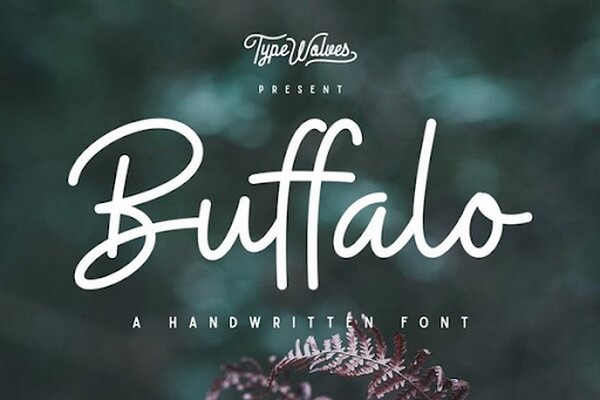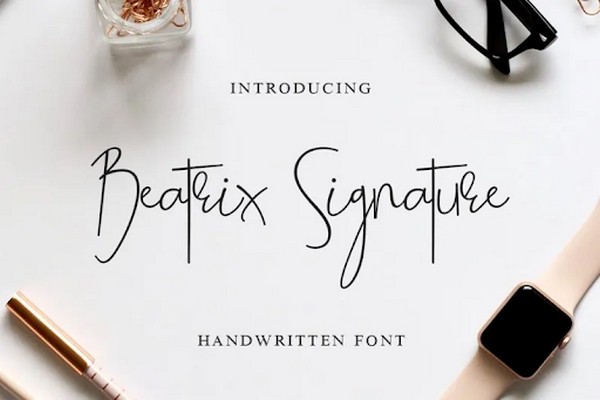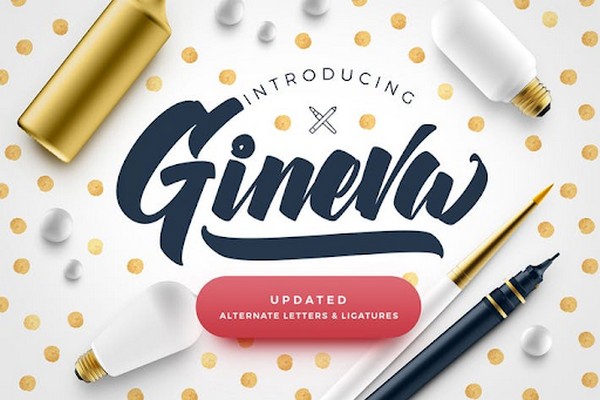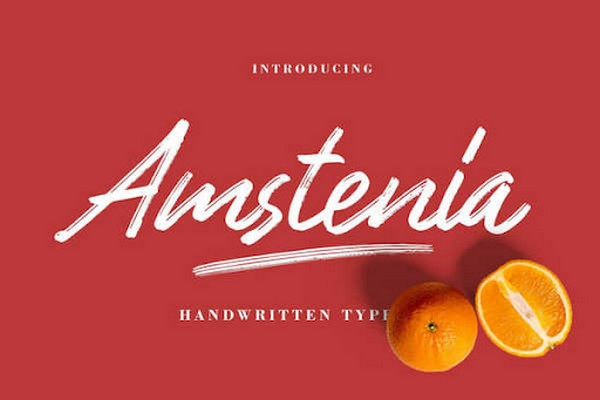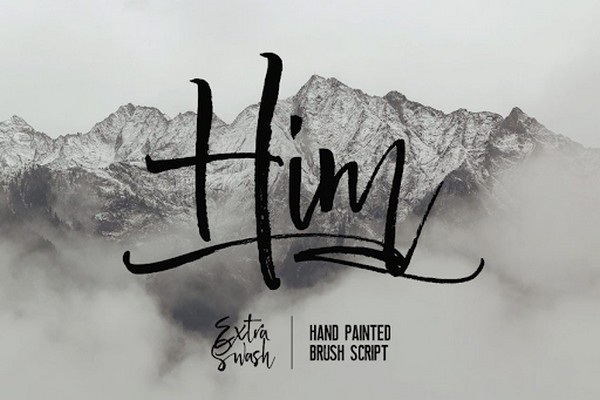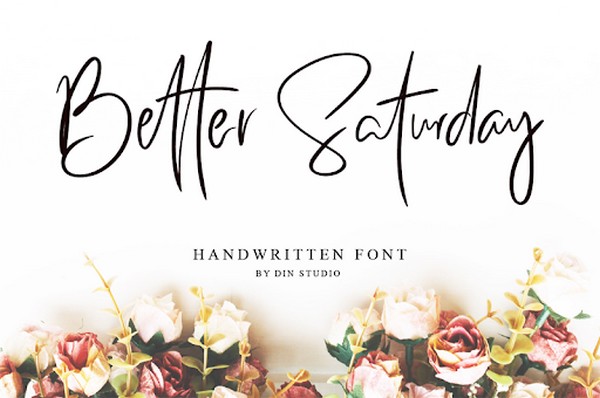
Font chữ viết tay là gì? Top những font chữ viết tay đẹp nhất hiện nay
Có thể nói chữ viết tay là một loại nghệ thuật vô cùng đẹp mắt đối với bất kể ai quan tâm đến chữ thư pháp. Những người “thợ” đã rất tỉ mỉ và hello88.con để có thể tạo ra những nét chữ đẹp mang đầy cảm xúc. Trong heloo88 nói riêng bạn cũng có thể sử dụng những font chữ viết tay để giúp sản phẩm của mình có tính nghệ thuật hơn. Hãy cùng chúng tôi tìm hiểu font chữ viết tay là gì và top những font chữ viết tay đẹp qua bài viết dưới đây bạn nhé!
Font chữ viết tay là gì?
Font chữ viết tay là một bộ font chữ mà khi ta đánh chữ vào thì nó sẽ hiện ra các dòng chữ giống như người thật viết. Nếu như các font chữ mặc định của Windows như Time New Roman, Arial không thể tạo nên cảm xúc gì thì các font chữ viết tay sẽ cho bạn cảm giác thân thiện, gần gũi trong từng đường nét. Còn gì tuyệt hơn khi mà heloo88 một tấm thiệp mà dùng font chữ viết tay. Cầm tấm thiệp trên tay người đọc sẽ có cảm giác vô cùng gần gũi và thân thiết.
Chữ viết tay với đặc trưng bởi sự tự nhiên được thể hiện nét riêng của từng người. Với font chữ này bạn có thể cảm nhận được sự gần gũi, thân thiết của nó qua từng đường nét. Dù là mang tính nghệ thuật hay phong cách trang trí thì font chữ viết tay cũng thực hiện vô cùng tốt với vai trò của mình, để mang đến những tác phẩm ý nghĩa và giá trị đến với người tiêu dùng.
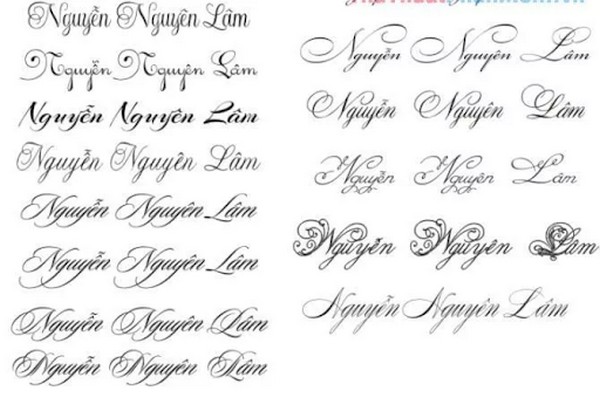
Font chữ viết tay là gì? Top những font chữ viết tay đẹp nhất hiện nay
Font chữ viết tay là gì?
Font chữ viết tay khá đa dạng về kích thước, phong cách, kiểu dáng, mang lại cho khách hàng nhiều lựa chọn và sự thoải mái trong sáng tạo. Nét đẹp về hình thức qua từng đường nét sẽ là điểm cộng khá lớn cho tác phẩm của bạn, vì thế việc lựa chọn font chữ viết tay sẽ là một trong những quyết định vô cùng đúng đắn để bạn có thể tạo ra một sản phẩm đặc trưng.
Font chữ viết tay có những tính năng ưu việt gì?
Đối với các ngành trong thời đại 4.0 như heloo88 đồ họa, quảng cáo thì những bộ font chữ này mang đến cho bạn vô số những đôi mắt đẹp, phù hợp và sáng tạo. Bên cạnh đó bạn còn có thể sử dụng nó cho việc soạn thảo văn bản như word, excel hoặc một số phần mềm đánh máy thông thường khác.
Chữ viết tay giúp mang lại lợi ích to lớn cho người dùng bởi tính đa năng cùng mục đích sử dụng phong phú làm banner, thiếp chúc mừng, thiệp đám cưới hay làm banner.
Nằm trong những bộ font chữ tiếng Việt chuẩn và được phát triển bởi những nhà heloo88 đồ họa lừng danh trên thế giới về các font chữ viết tay đẹp. Tất cả đều có xuất xứ thuộc vào hàng khủng bởi lịch sử hình thành và phát triển của chúng.
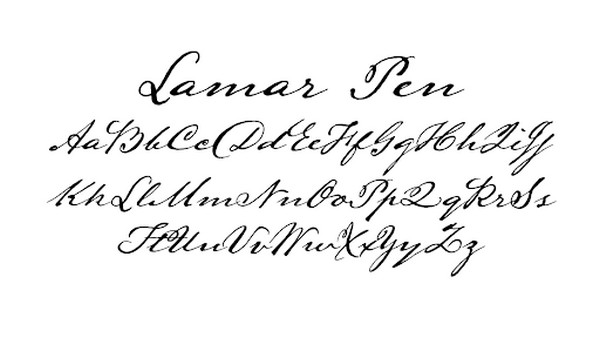
Font chữ viết tay là gì? Top những font chữ viết tay đẹp nhất hiện nay
Ngày nay, font chữ viết tay là một dạng tài nguyên, là kho tàng quý báu không chỉ dành riêng trong lĩnh vực heloo88, sáng tạo mà nó còn được sử dụng đa dạng trong nhiều lĩnh vực khác nhau.
Top các font chữ viết tay đẹp mà bạn nên biết
Ngoài những font chữ thông thường cho công việc hàng ngày thì đôi khi bạn cũng cần đến những font chữ viết tay, hỗ trợ tiếng để tự mình heloo88 những tấm thiệp, những lời chúc dành cho bạn bè, người thân hay bất kỳ mục đích sử dụng nào khác. Bạn sẽ khiến người khác phải ngỡ ngàng khi những văn bản soạn thảo đó có chữ viết tay cực đẹp, cực chất lượng.
Font chữ Amber Queen Signature
Khám phá và tận hưởng thế giới sáng tạo một cách hoàn hảo. Phông chữ Amber Queen Signature là một font chữ được viết tay độc đáo với các ký tự sắc nét và góc cạnh. Cho dù bạn là một nhà heloo88 đồ họa hay một nhà sáng tạo có gu thẩm mỹ thì bạn cũng sẽ thích phong cách hello8862 com và sôi động này.
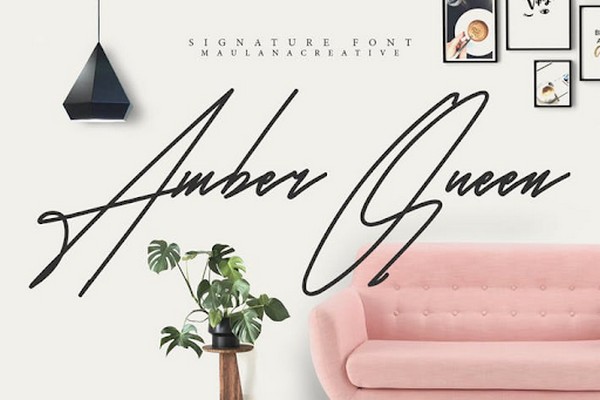
Font chữ viết tay là gì? Top những font chữ viết tay đẹp nhất hiện nay
Font chữ Leah Gaviota Hand Lettered
Sử dụng font chữ Leah Gaviota Hand Lettered để thêm giao diện thú vị cho bài viết của bạn. Font chữ viết tay này là sự kết hợp hài hòa của các kiểu script, chữ in đậm và cả sans- serif. tất cả đều cho ra một bộ văn bản hay thư, thiệp thủ công hoàn hảo. Một gói sẽ được tặng thêm 1 bộ 100 hình minh họa dễ thương. Có thể được dùng để heloo88 bài nhóm, thư từ hoặc thiệp,…
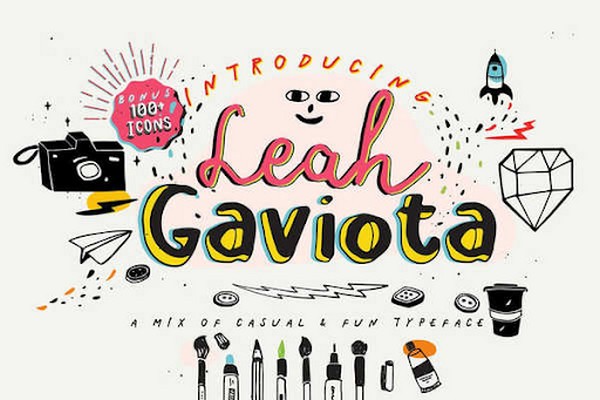
Font chữ viết tay là gì? Top những font chữ viết tay đẹp nhất hiện nay